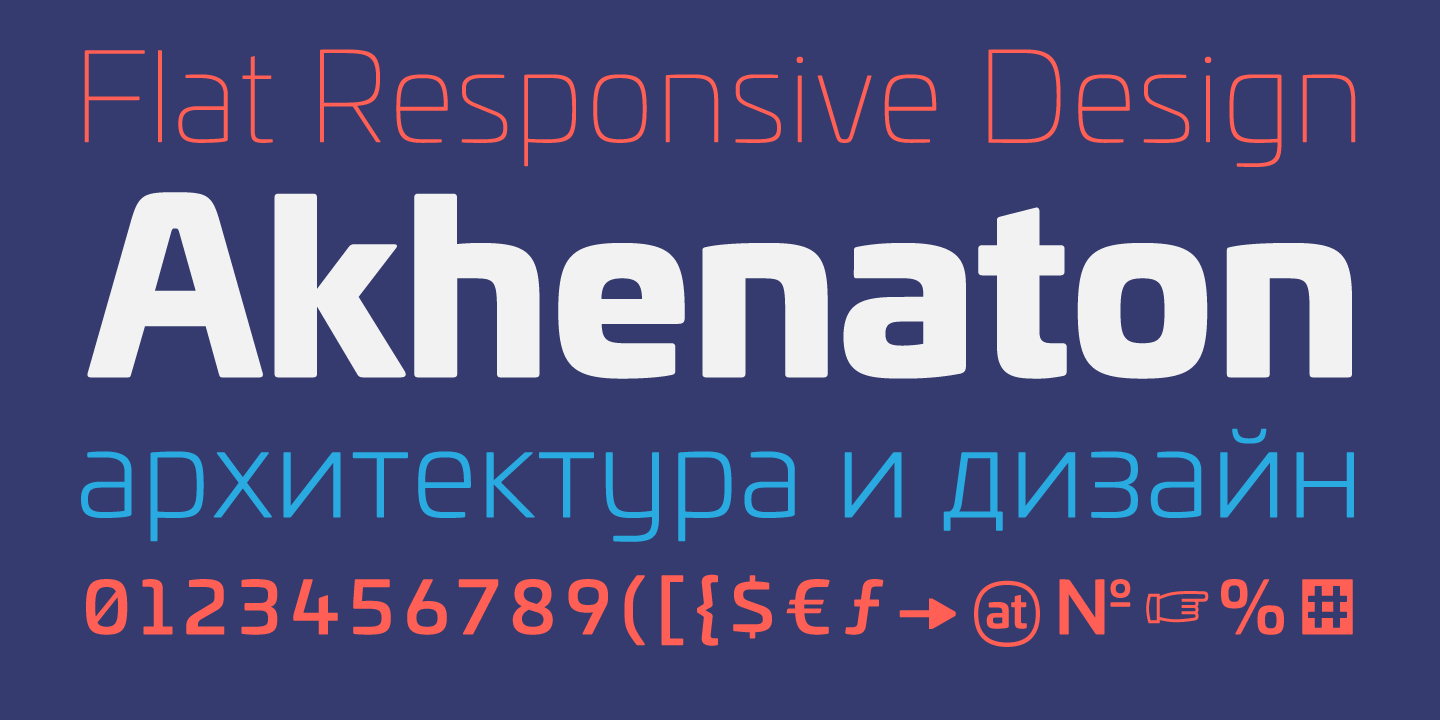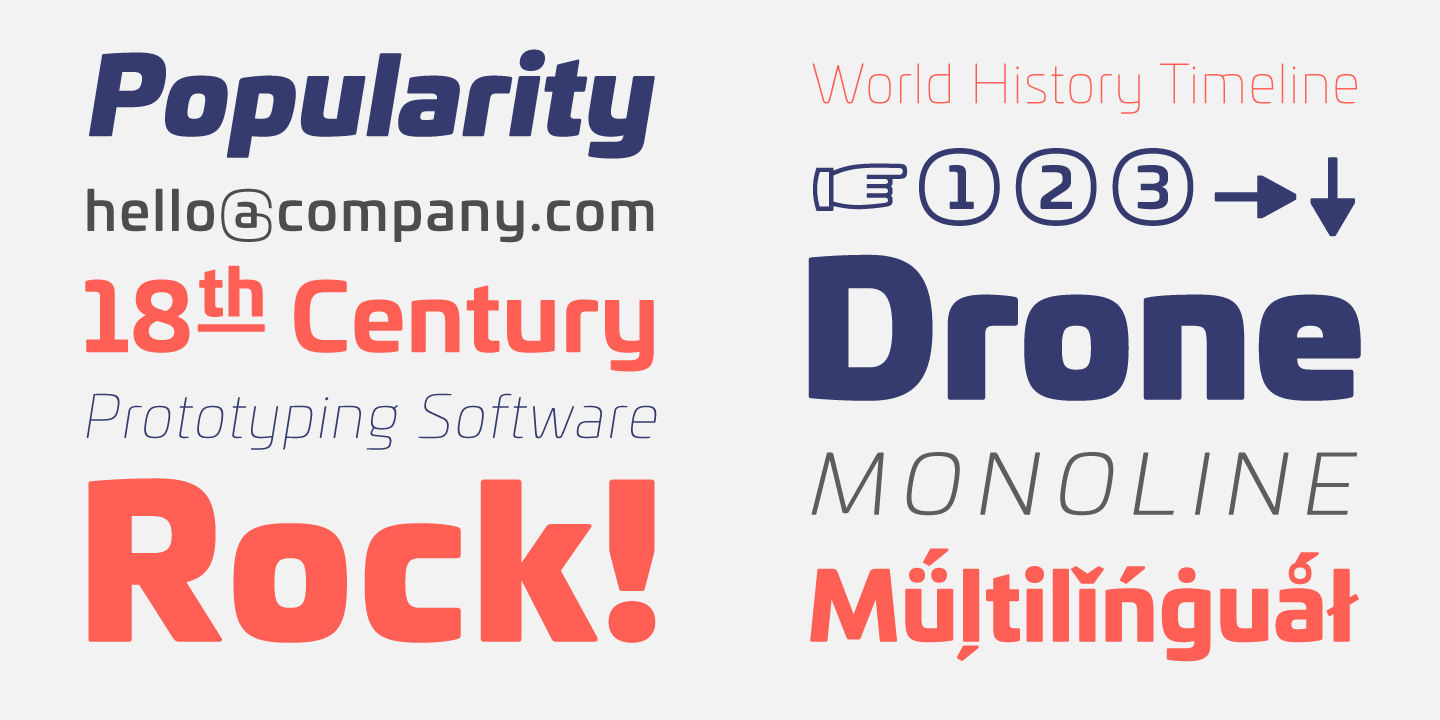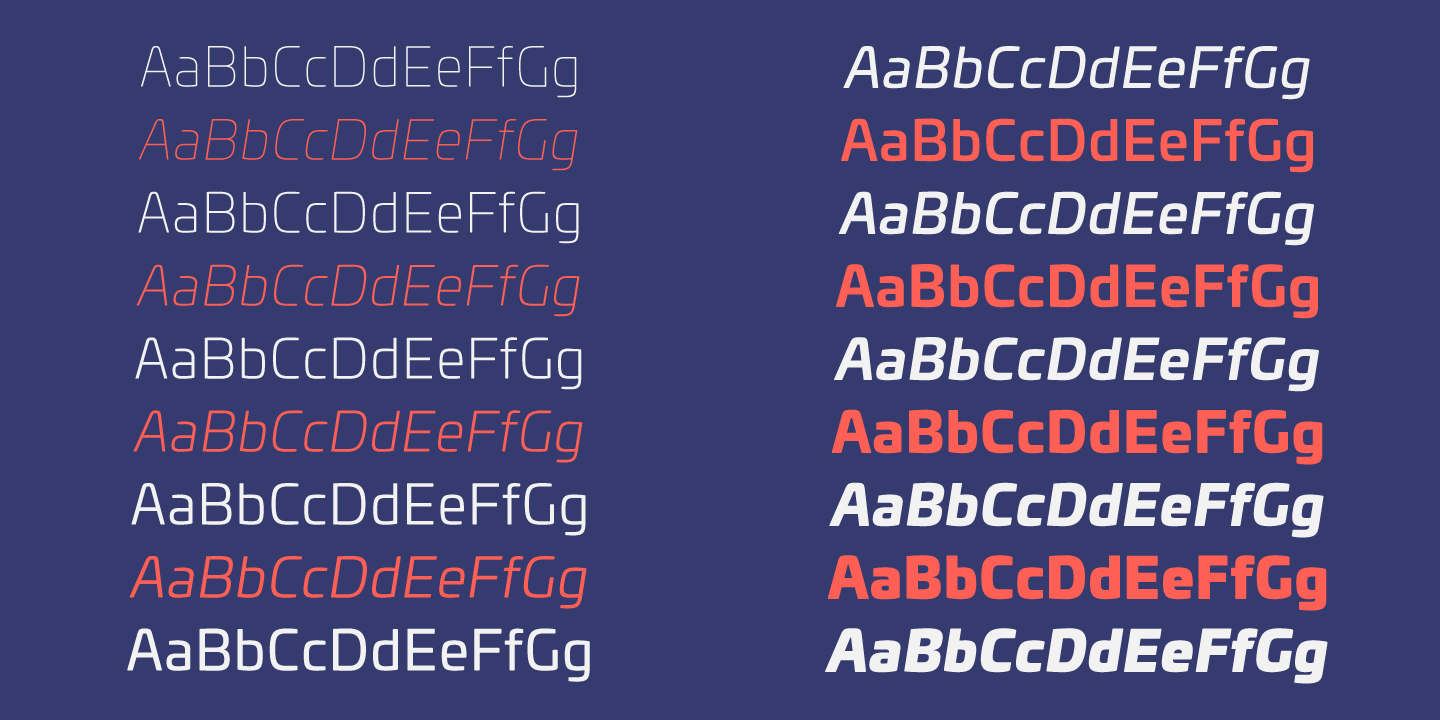
Univia Pro ist eine serifenlose Schriftfamilie von Olivier Gourvat und erschien 2015 über dessen Label Mostardesign Type Foundry. Die Familie verfügt über neun Strichstärken mit Kursiven. Die Schnitte besitze eine erweiterte lateinische und kyrillische Belegung.